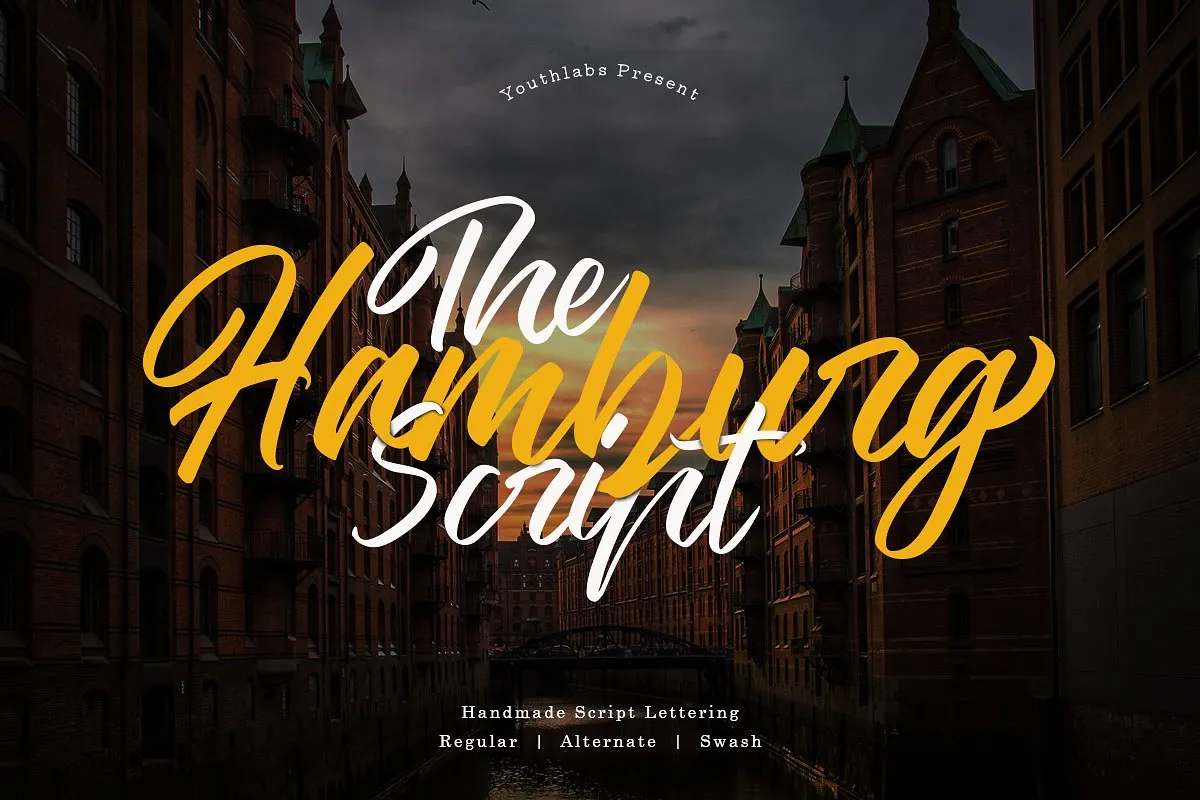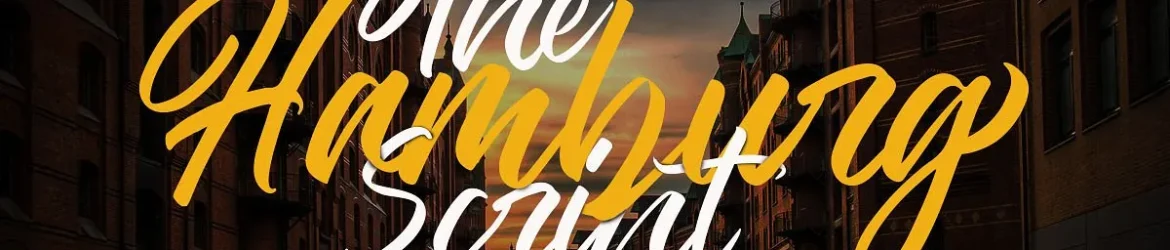
Esta é uma nova tipografia moderna inspirada na escritura artística tradicional. As letras deste tipo também se mostram suaves com um estilo simples. Introduzimos a Hamburg Font, que surgiu do design de Calligrafia Script Tradicional, usando o pincel de uma pena. Este font foi meticulosamente feito à mão através da escrita e desenho manual, utilizando-se apenas de uma pena. É perfeito para qualquer tipo de design, seja um logo, um site ou até mesmo um projeto gráfico em seu blog. Se você está procurando por uma tipografia que combine elegância com modernidade, a Hamburg Script Font é algo que precisa ser considerado.